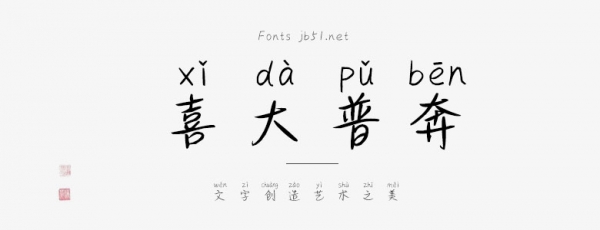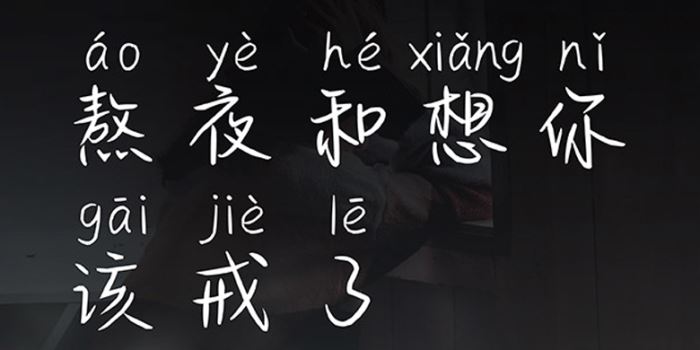
方正手跡-熬夜和想你該戒了由方正字庫宋昱東設(shè)計師出品的藝術(shù)字體,該字正文漢字轉(zhuǎn)折多用圓角,結(jié)構(gòu)輕松有趣,搭配英文拼音更顯活潑可愛,適合應(yīng)用于藝術(shù)設(shè)計、平面宣傳設(shè)計、網(wǎng)頁設(shè)計,書法等領(lǐng)域。
字體介紹
熬夜和想你該戒了是一款拼音體,正文漢字轉(zhuǎn)折多用圓角,結(jié)構(gòu)輕松有趣,搭配英文拼音更顯活潑可愛。適用于少年兒童類書刊、綜藝影視字幕用字、漫畫用字,以及社交網(wǎng)絡(luò)的個性化用字。。